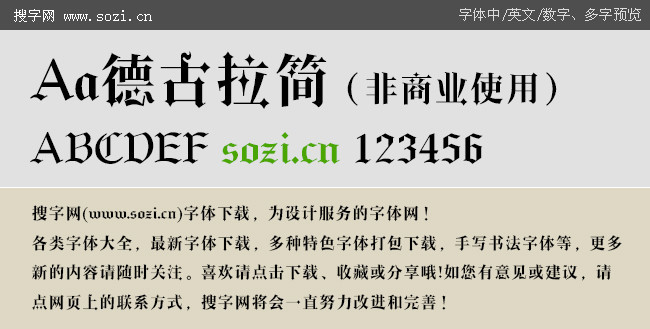
Aa德古拉簡(jiǎn)
搜字網(wǎng)給大家提供一款A(yù)a德古拉簡(jiǎn)(非商業(yè)使用)字體下載,該字體是一款不錯(cuò)的藝術(shù)字體,這款字體風(fēng)格比較有特色,清新簡(jiǎn)明,具有很好的視覺(jué)感。適合書裝設(shè)計(jì)、包裝設(shè)計(jì)、海報(bào)設(shè)計(jì)等應(yīng)用(此字體為個(gè)人非商用版,商用可以聯(lián)系QQ:1006760504)。